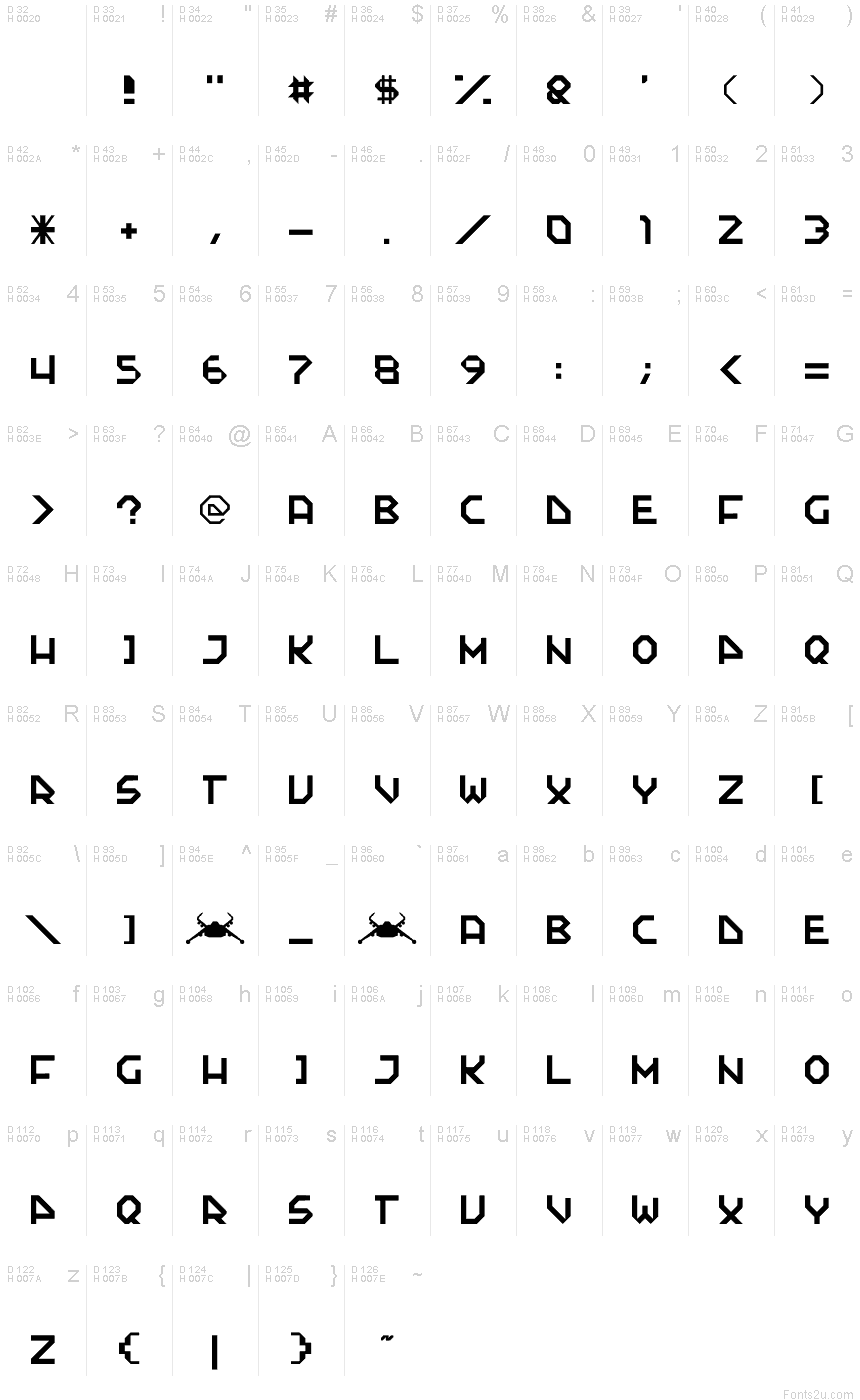
Descent ][ è un font techno display gratuito che sembra scolpito nel metallo e collegato a un pannello di controllo. Gli angoli affilati e angolari si uniscono in aste alte e rigide, dando a ogni parola un tocco meccanico, quasi industriale. La geometria quadrata e serrata risulta futuristica senza cadere nel caos, così i tuoi titoli rimangono audaci, leggibili e inequivocabilmente digitali.
Usando Descent ][, puoi dare un tocco pulito e tecnico a loghi di giochi, poster sci-fi, flyer EDM, brand tecnologici, grafiche e-sport e sovrimpressioni per lo streaming. Il ritmo delle sue linee rette e delle diagonali tagliate risalta meravigliosamente nelle dimensioni grandi, dove ogni smusso e giuntura può respirare. Abbina questo font gratuito a un carattere sans serif semplice e neutro per il testo principale e lascia che Descent ][ gestisca i titoli e i loghi di grande impatto.